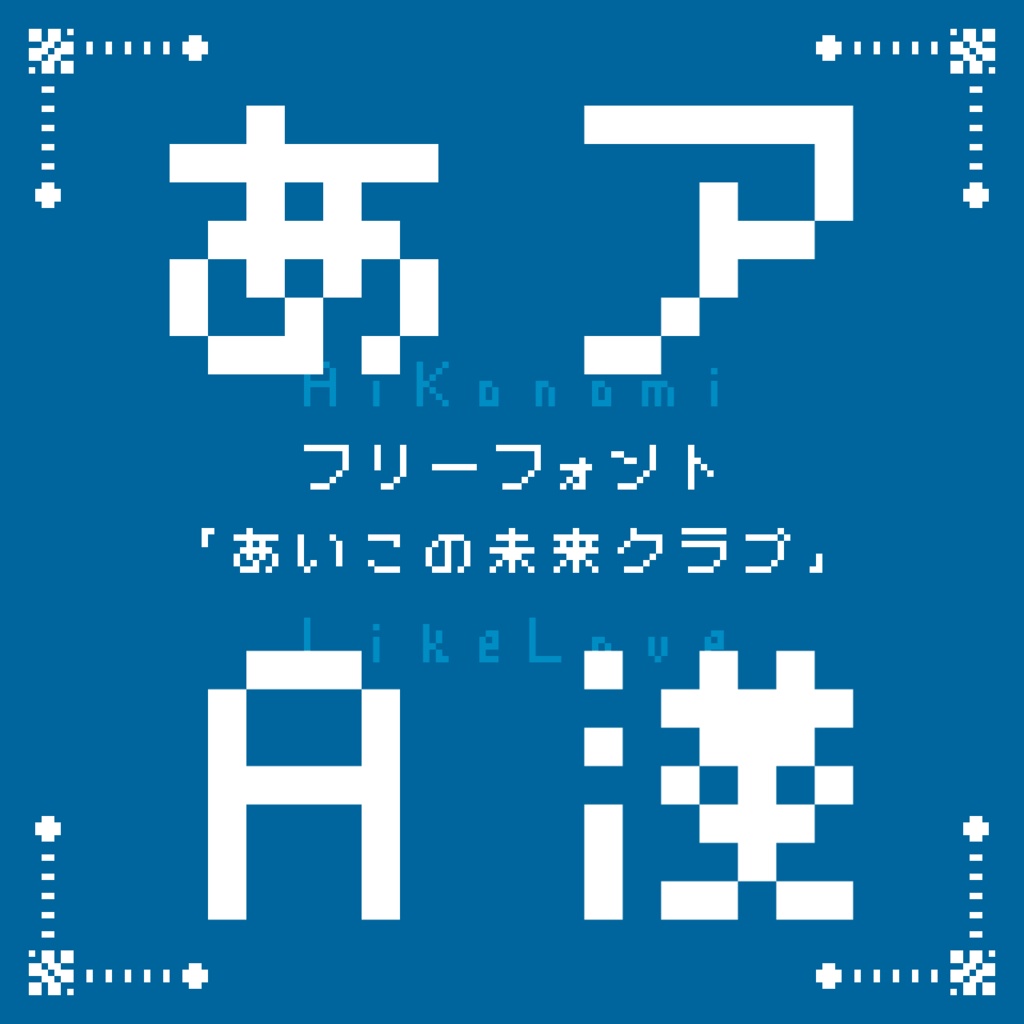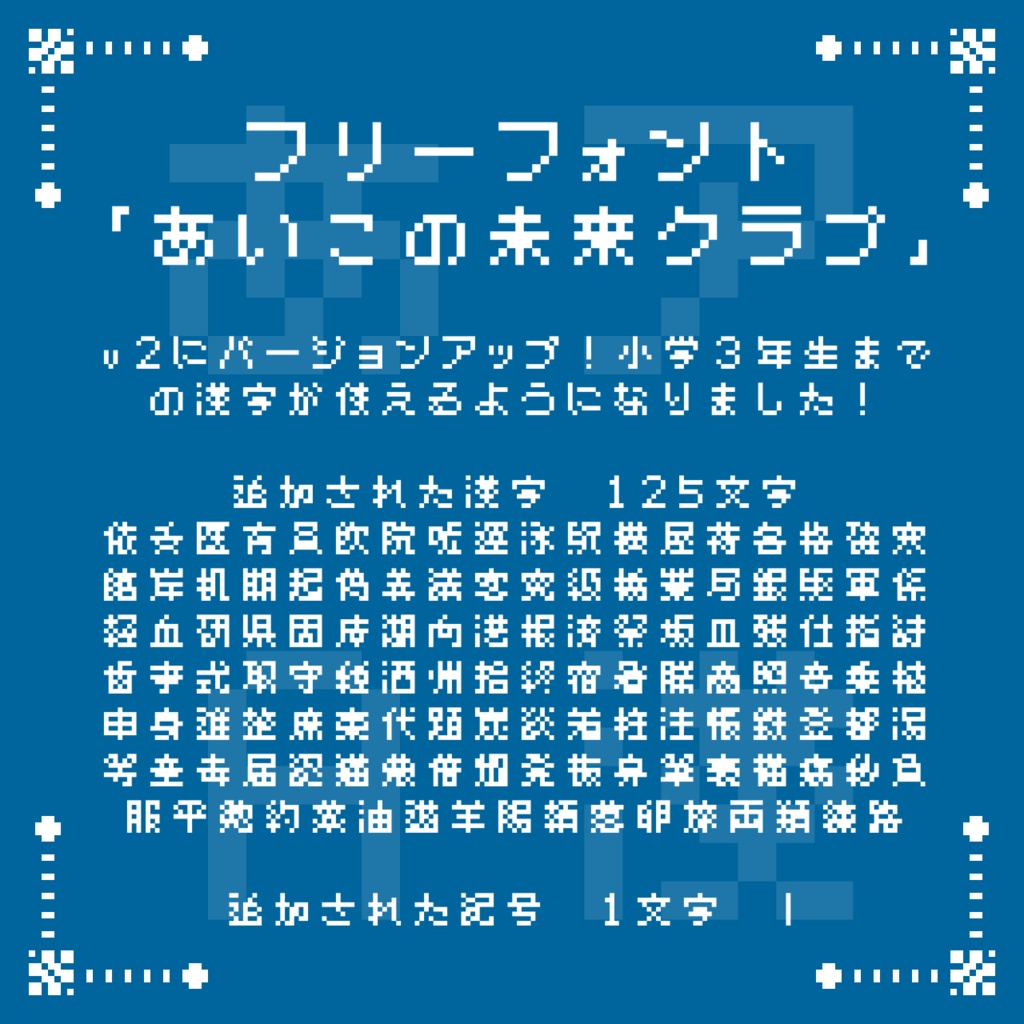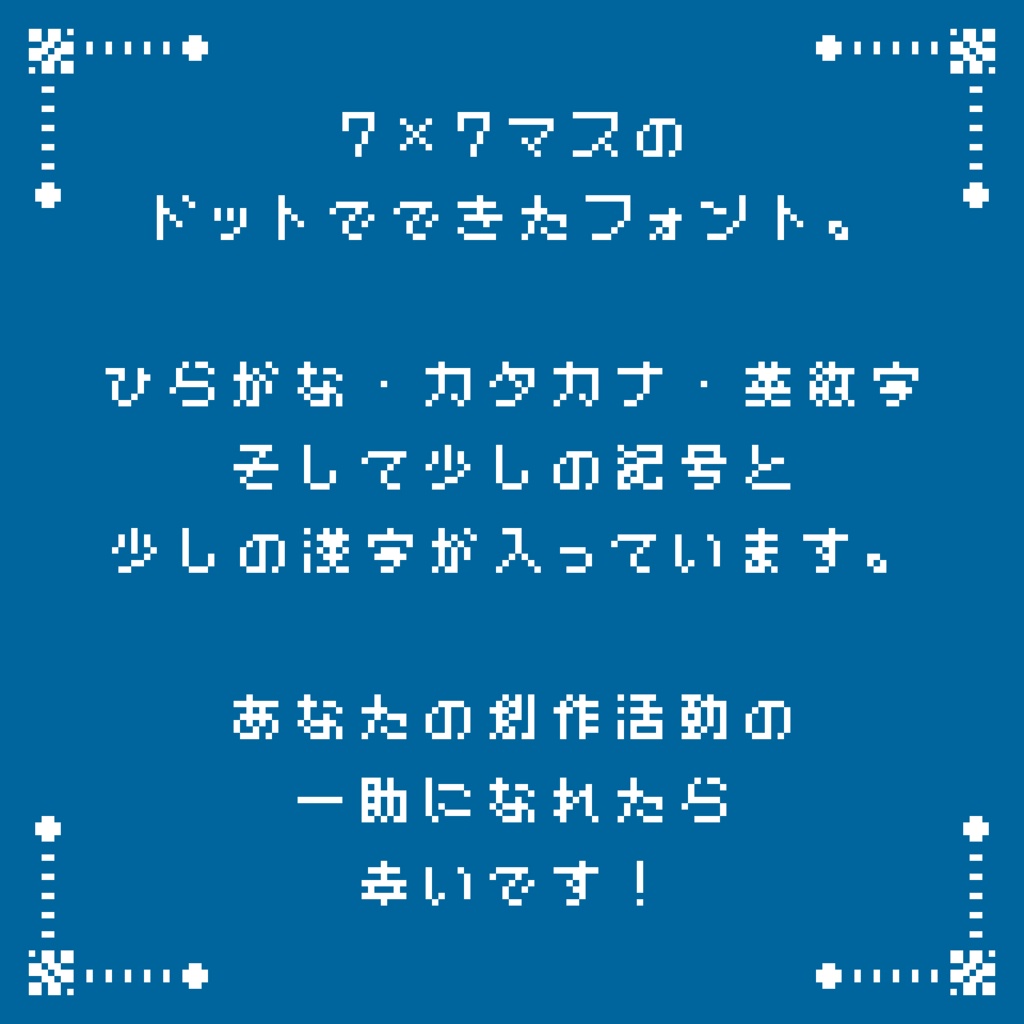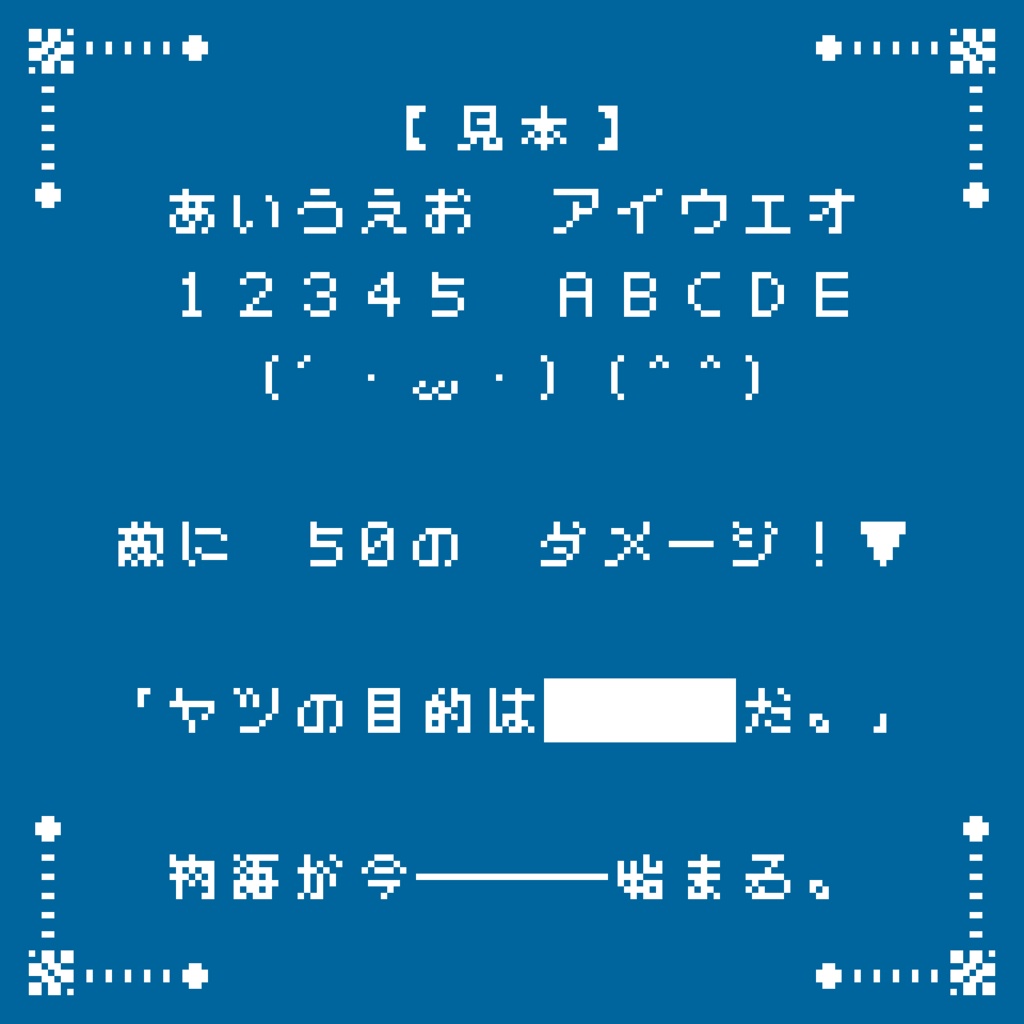
【無料あり】フォント「あいこの未来クラブ」
画像からフォントを制作する素敵なツール、SakuttoFont(https://toktaro.github.io/SakuttoFont/)の力を借りて生まれた、7×7マスのドットのオリジナルフォントです。 基本的に個人/法人、商用/非商用問わず、幅広くご利用いただけます。 zipファイルのダウンロード後、フォントのインストール前に同梱のreadmeを必ずご確認ください。 初期リリース版(上段の商品)とv2(下段)はそれぞれ単体でご利用可能です。また、「フォント、良かったよ」「制作お疲れ様」と思っていただいた際には、支援版をご購入いただけると大変嬉しいです。 以降の内容はreadmeとほぼ同様です。
2026/03/08 漢字125字、記号1字を追加したv2の公開。小学3年生までの漢字が打てるようになりました。追加された文字につきましては、BOOTH上の画像またはreadmeをご確認ください。 2025/11/25 データ改変と再配布についてのreadmeの追記。 2025/11/24 公開
あいうゔえおかきくけこがぎぐげごさしすせそざじずぜぞたちつてとだぢづでどなにぬねのはひふへほばびぶべぼぱぴぷぺぽまみむめもやゆよらりるれろわゐゑをんぁぃぅぇぉゃゅょっゎアイウヴエオカキクケコガギグゲゴサシスセソザジズゼゾタチツテトダヂヅデドナニヌネノハヒフヘホバビブベボパピプペポマミムメモヤユヨラリルレロワヰヱヲンァィゥェォャュョッヮ ABCDEFGHIJKLMNOPQRSTUVWXYZabcdefghijklmnopqrstuvwxyz 一引右羽雨雲円園遠王黄音下何夏家科歌火花画会回海絵貝外角学楽活間丸岩顔帰気汽記休弓牛魚京強教玉近金九空兄形計月犬見元原言古戸五午後語交光公口工広校考行高合国黒今左才細作三山算四姉子市思止糸紙字寺時耳自七室社車弱手首秋週十出春書女小少上場色食心新森親人図水数星晴正生声西青石赤切雪先千川線船前組早草走足村多太体台大谷男知地池竹茶中昼虫朝町長鳥直通弟天店点田電土冬刀東当答頭同道読内南二肉日入年馬買売白麦八半番百父風分文聞米歩母方北本妹毎万名明鳴毛木目門夜野矢友夕曜用来理里立力林六話悪安暗医委意育員院飲運泳駅央横屋温化荷界開階寒感漢館岸起期客究急級宮球去橋業曲局銀区苦具君係軽血決研県庫湖向幸港号根祭皿仕死使始指歯詩次事持式実写者主守取酒受州拾終習集住重宿所暑助昭消商章勝乗植申身神真深進世整昔全相送想息速族他打対待代第題炭短談着注柱丁帳調追定庭笛鉄転都度投豆島湯登等動童農波配倍箱畑発反坂板皮悲美鼻筆氷表秒病品負部服福物平返勉放味命面問役薬由油有遊予羊洋葉陽様落流旅両緑礼列練路和亜哀愛闇杏位依異胃衣印因宇嘘唄映永英詠液演縁凹億憶乙俺仮加可過我解壊快怪悔械各格確覚叶刊完汗環甘願喜器奇希机機偽技義議吉救泣旧巨拒許共恐狂暁極均禁句駆軍径景系欠結件幻源玄現限個固己功好攻江甲稿紅香告困佐座再最済載在材桜札殺参残士師志支枝氏私肢視治磁鹿失朱種呪樹周汁祝術旬巡初唱招晶照笑丈情信臣辛刃垂推寸瀬性成清精聖静席跡設説占専戦泉浅旋創倉奏争像造則即束属続存尊誰単担団断段宙挑超痛低敵的伝怒桃灯闘毒独凸届認猫巴派敗杯背抜判版否彼柊描苗不夫富布怖丙並閉別変編包報宝崩法豊亡忘望某僕魔枚抹末満未民夢無戻約与妖欲頼卵陸律了料良涙類令冷老呟 _--—ー〜・・, ,、; ;:‼︎⁉︎! !? ?….。'‘’'""(())[[]]「」【】@@**/\&&##%%※ ``´ ^ ^°℃↑↓→←++÷×>><<≦≧≫=≠≒−~□■▲△▼▽◆◇○◎☆★♡♪ ⬛︎々$$|¥¥ω〇12345678901234567890 漢字は小学三年生までに習う漢字+みーてぃあが独断で入れた漢字が入っています。略字あり。一部の記号は複数が同じ見た目であったり、全角を打つと半角で出てきます(その逆もあります)。